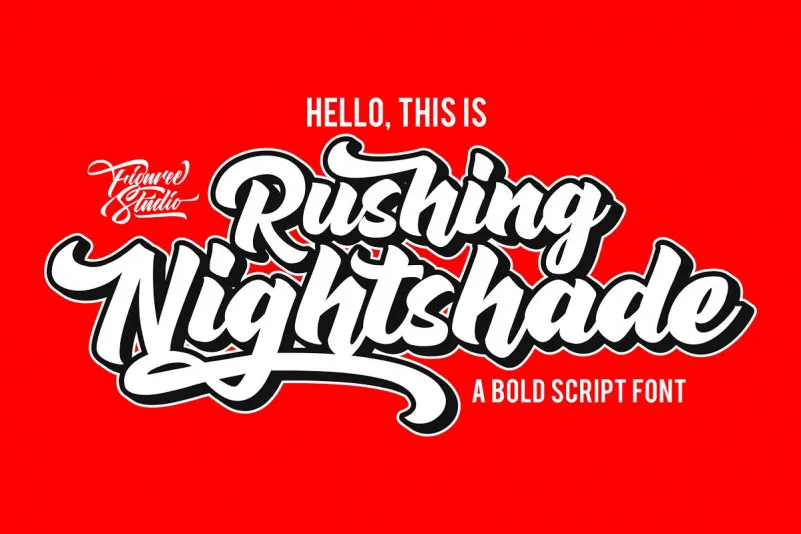
Rushing Nightshade Script Font – Download Grátis
A Rushing Nightshade Script Font é uma moderna tipografia bold que traz um toque divertido para criar conteúdo atraente e chamativo. Introduzida pela figurae studio, ela se destaca como uma script naturalmente grosso, inspirado no estilo vintage. A fonte foi criada combinando características de letra à mão, resultando em movimento dramático que é perfeito para qualquer próxima ideia criativa que precise de um toque retro ou moderno. Perfeita tanto para logotipos quanto para citações escritas a mão, encaixa-se bem no design de embalagens de produtos, cabeçalhos e pôsteres. Também é uma escolha ótima para os materiais de merchandising, redes sociais e cartões de felicitações. Com a Rushing Nightshade Script Font, você pode trazer um toque único à sua próxima criação visual, mantendo sempre uma essência vintage ou moderna ao mesmo tempo.